이 기사에서는 작업에 현대적인 감각을 더하려는 디자이너를 위한 최고의 산세리프 글꼴을 살펴보겠습니다. sans-serif 글꼴은 화면에서 더 쉽게 읽을 수 있기 때문에 디지털 디자인에 선호되는 경우가 많다는 사실을 알고 계셨습니까? 실제로 웹에서 가장 많이 사용되는 글꼴 중 하나인 Arial은 산세리프체입니다.
따라서 웹사이트 디자인 작업을 하든 인쇄 광고를 제작하든 최고의 산세리프체 목록에서 선택할 수 있는 다양한 옵션을 제공합니다.
최고의 프리미엄 산세리프체
디자인 프로젝트를 다음 단계로 끌어올릴 수 있는 고품질 글꼴을 특징으로 하는 30개의 최고의 Sans Serif 글꼴 블로그 게시물의 최고의 프리미엄 글꼴 섹션을 소개합니다. 최고의 글꼴 옵션을 확인하고 디자인을 더욱 향상시키십시오.
애빙턴
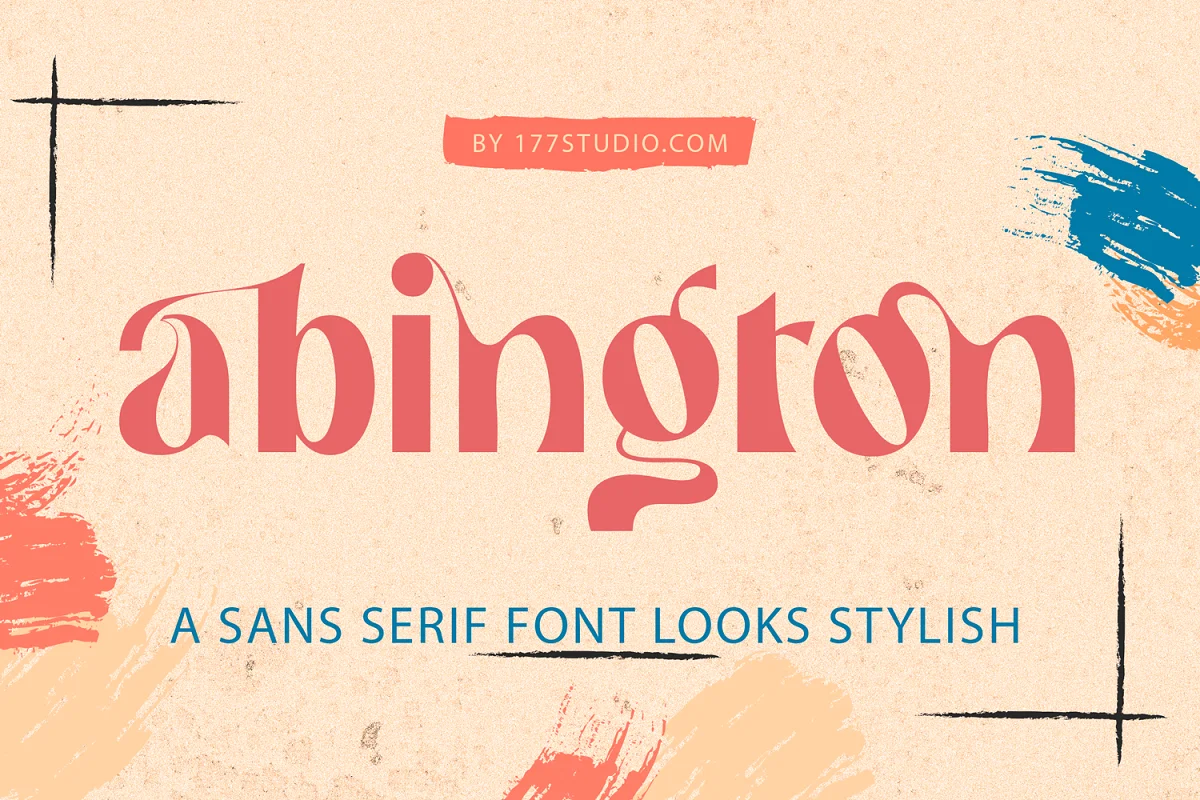
애빙턴은 우아하면서도 모던함과 고풍스러움을 동시에 느낄 수 있는 매력적이고 스타일리시한 모던 서체입니다.
이 산세리프 글꼴은 세련미를 발산하여 브랜딩 프로젝트, 로고, 소셜 미디어 게시물, 광고, 제품 포장, 사진, 초대장, 편지지 및 손글씨 터치가 필요한 모든 프로젝트에 적합합니다.
Abington의 견고한 디자인은 시선을 사로잡으며 읽기 쉽습니다. 그 매력적이고 고풍스러운 스타일은 모든 프로젝트에 개성을 더하는 동시에 우아함의 요소를 유지합니다. 이 글꼴은 전문성을 희생하지 않고 디자인에 개성을 더하고 싶은 사람들에게 적합합니다.
주축대
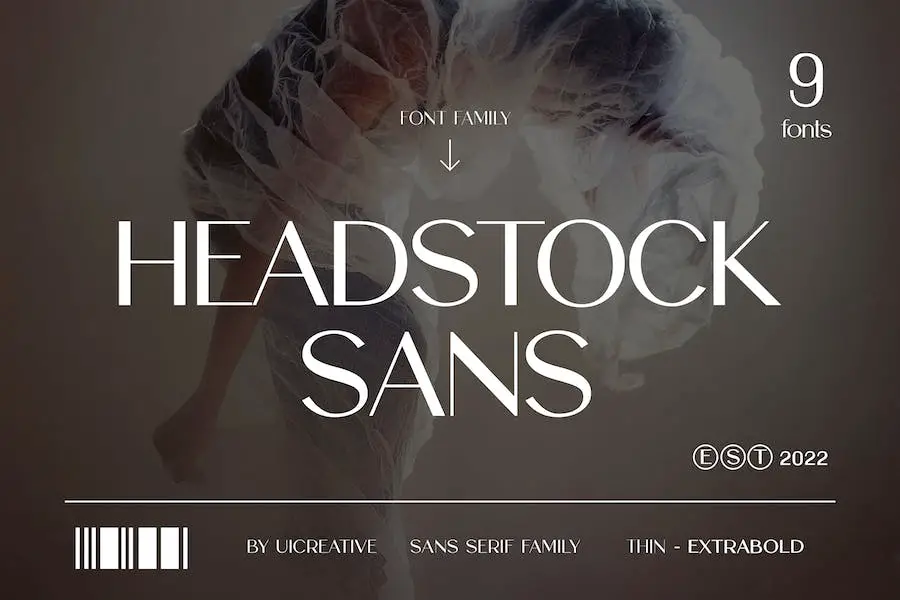
Headstock은 9가지 두께로 제공되는 새로운 Sans Serif 패밀리 글꼴입니다. 현대적이고 우아한 스타일로 문구, 타이포그래피 인용구, 잡지 또는 책 표지, 웹사이트 헤더, 의류, 브랜딩, 포장 디자인 등 다양한 프로젝트에 적합합니다.
남성성과 여성성을 모두 보여주어 패션 관련 브랜딩이나 편집 디자인에 적합합니다.
Google Sans Serif 글꼴에 최적화된 Headstock은 깨끗하고 현대적인 디자인의 현재 트렌드에 완벽하게 맞습니다. 다재다능함과 우아함을 갖춘 이 글꼴은 프로젝트를 향상시키려는 많은 디자이너에게 확실한 글꼴입니다.
에스포르티카
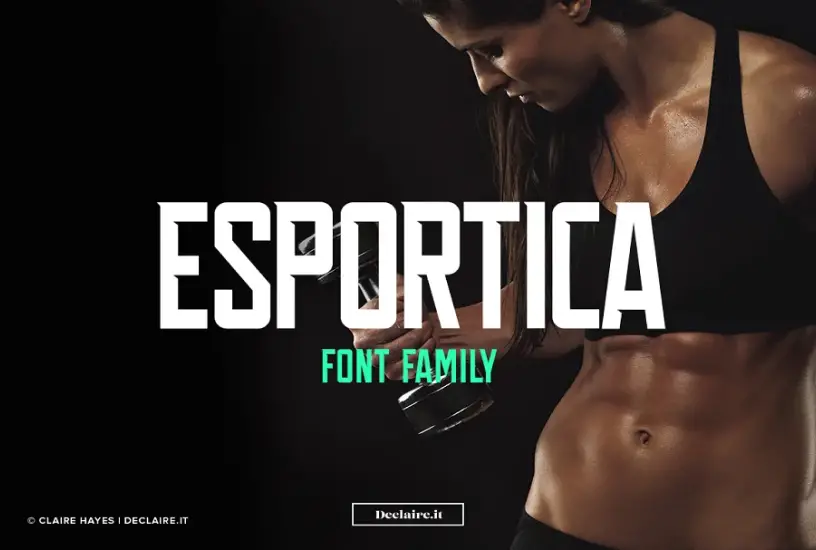
Esportica는 헤드라인에 현대적인 감각을 더할 수 있는 환상적인 디스플레이 서체입니다. 이 서체에는 대문자와 소문자, 구두점, 숫자 등 230개의 글리프가 포함되어 있습니다.
또한 Esportica는 다양한 국제 언어를 지원하므로 디자이너를 위한 다재다능한 글꼴입니다.
Adobe Sans Serif 글꼴과 관련하여 Esportica는 깔끔한 선과 매끄러운 모양으로 인해 탁월한 선택입니다. 날카로운 모서리와 대담한 글자가 있는 이 서체는 모든 디자인 프로젝트에 새로운 수준의 전문성을 제공할 수 있습니다.
풍카시
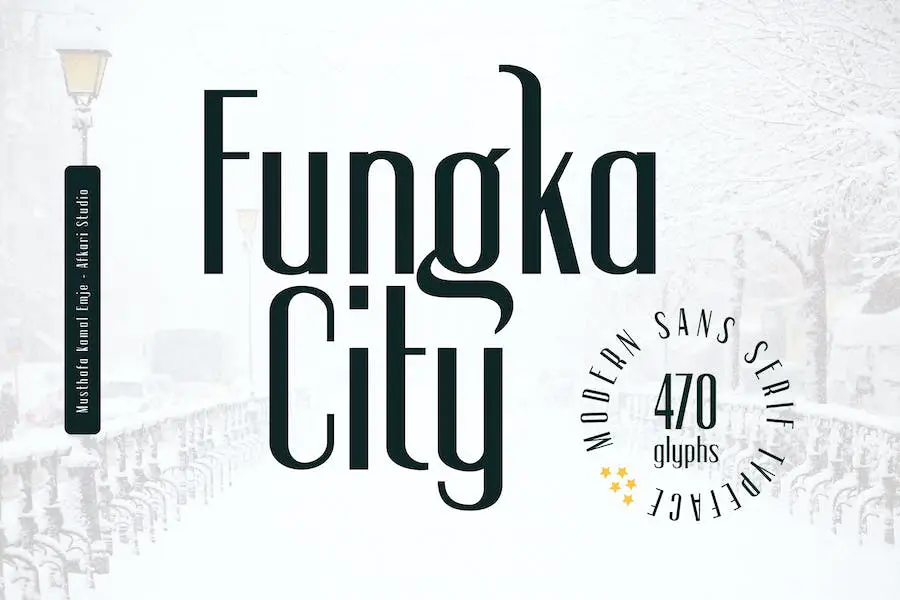
Fungka City는 디자인에 개념적 우위를 부여하는 현대적이고 세련된 산세리프 글꼴입니다. 다른 현대 산세리프체와 잘 어울리지만 독특한 교대 문자와 세련된 악센트로 인해 그 자체로도 두드러집니다.
Word 문서에 사용할 다재다능하고 세련된 산세리프 글꼴을 찾고 있다면 Fungka City를 확실히 고려해 볼 가치가 있습니다. 독특한 디자인과 광범위한 기능으로 인해 모든 디자이너의 툴킷에 추가할 수 있습니다.
메티큘라
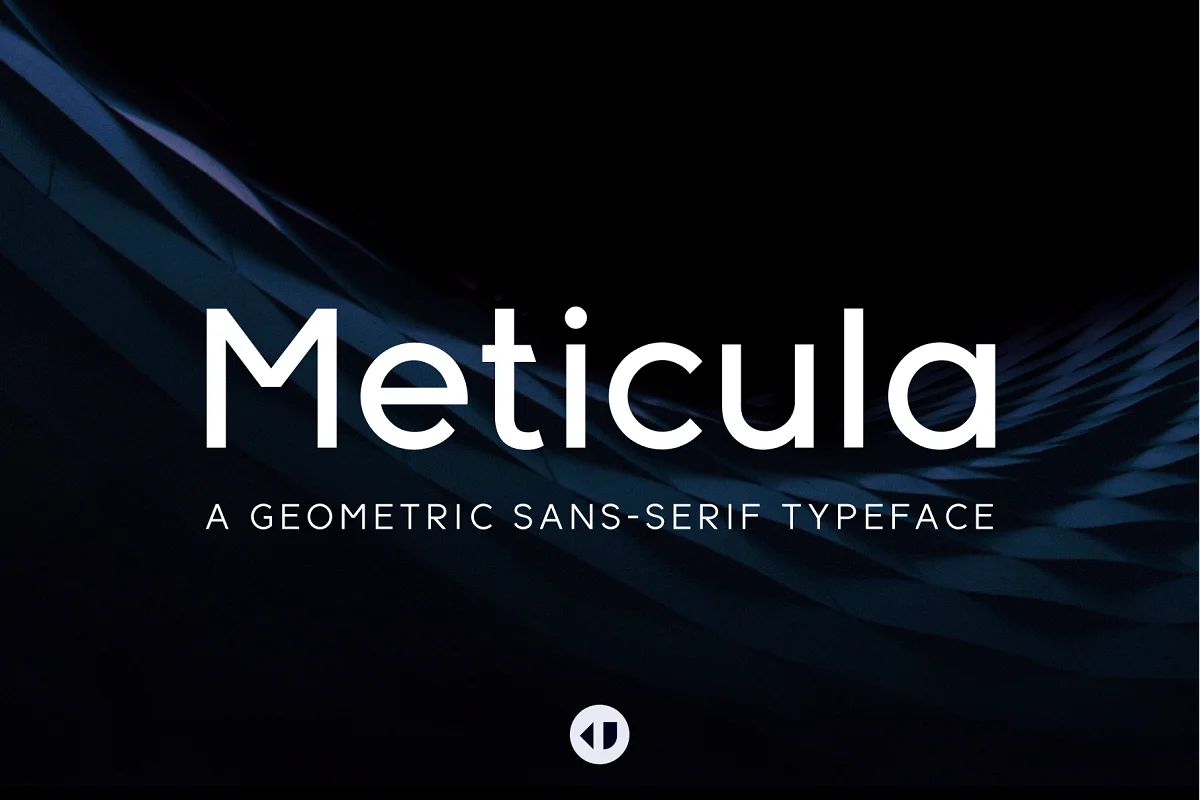
Meticula는 기하학적 모양과 현대적인 타이포그래피를 결합한 다목적 산세리프 글꼴 모음입니다. 18개의 글꼴로 구성되어 있으며 각 글꼴은 모든 유형의 그래픽 디자인 및 타이포그래피 작업에 적합하도록 세심하게 제작되었습니다.
미니멀한 디자인과 다양한 글꼴 스타일을 갖춘 Meticula는 Canva 프로젝트에 사용할 완벽한 산세리프 글꼴을 찾는 그래픽 디자이너에게 탁월한 선택입니다. 글꼴 패밀리의 깔끔한 선과 균형 잡힌 비율은 눈에 띄는 전문적인 디자인을 만드는 데 이상적입니다.
높은
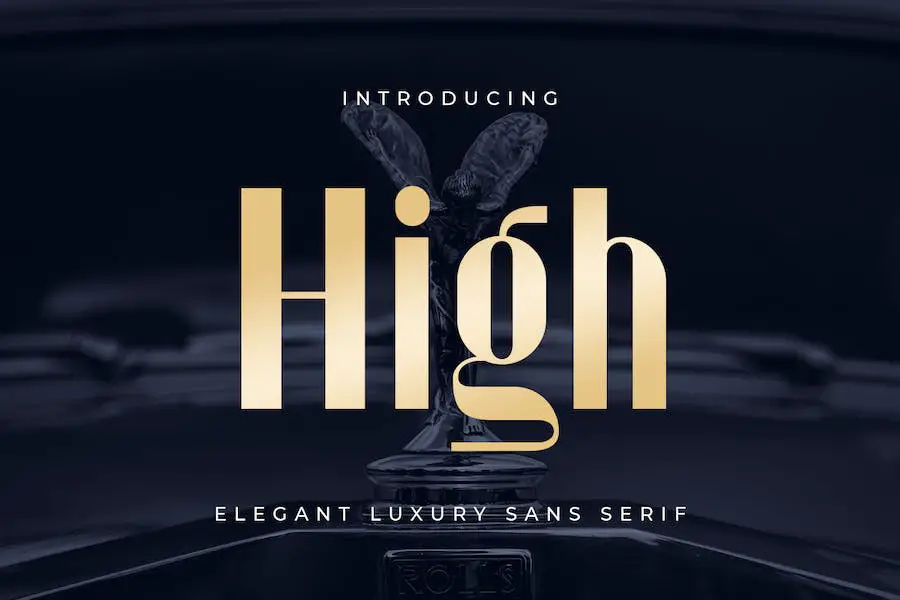
High는 우아한 프로젝트를 진행하는 사람들을 위해 특별히 제작된 새롭고 우아한 고급 산세리프 글꼴입니다.
고유한 모양의 추가 합자와 대체 글꼴이 있는 이 글꼴은 모든 브랜드에 가치를 더할 것입니다. High는 자신의 디자인을 더욱 우아하고 고급스럽게 보이게 하는 솔루션을 찾는 디자이너 또는 제품 소유자를 활용하는 데 도움이 될 수 있습니다.
결론적으로 High는 우아하고 고급스러운 산세리프 글꼴을 찾는 사람에게 환상적인 선택입니다.
고유한 기능으로 인해 약간의 정교함이 필요한 고급 프로젝트 작업에 적합합니다. 브랜드나 프로젝트를 향상시킬 방법을 찾고 있다면 높음 사용을 고려하십시오.
클리오
클리오는 심플하고 깔끔한 선과 시각적인 우아함이 특징인 디스플레이용 산세리프체입니다. 로고, 제목, 잡지와 같은 우아한 테마의 디자인 프로젝트에 적합합니다. 표준 합자를 사용하여 사용자 지정 연결된 문자를 쉽게 만들 수 있습니다.
지노라
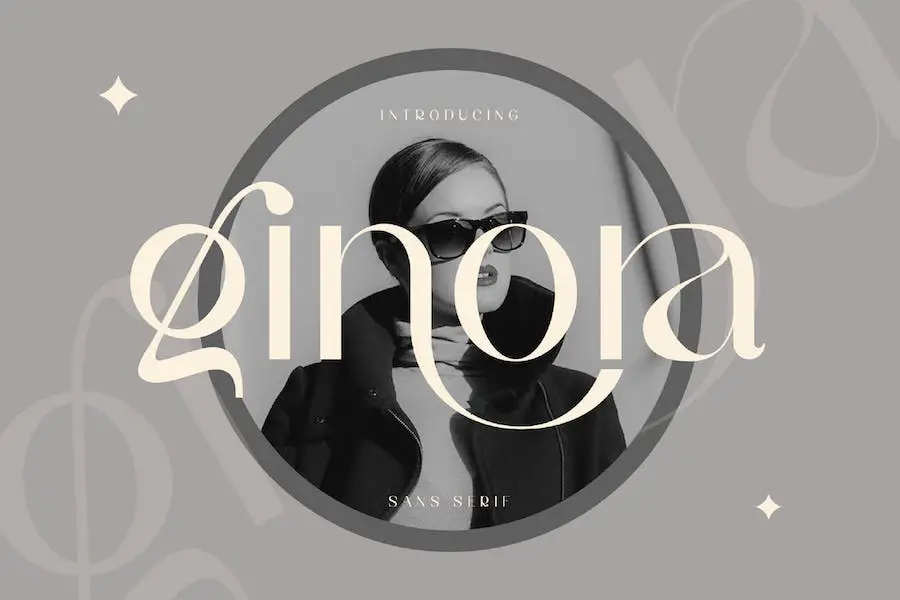
Ginora는 우아함과 품격을 풍기는 세련된 산세리프체입니다. 디자인에 모던함과 향수를 더하고 싶은 분들에게 적합합니다. 이 글꼴은 다목적일 뿐만 아니라 기능적이어서 잡지, 로고, 소셜 미디어 등에 사용하기에 이상적입니다.
결론적으로 Ginora는 프로젝트를 향상시키기 위해 새로운 산세리프 스타일을 찾는 디자이너에게 꼭 필요한 글꼴입니다. 우아하고 유행을 타지 않는 디자인으로 이 글꼴이 창작자들 사이에서 가장 인기 있는 글꼴이 된 것은 놀라운 일이 아닙니다.
숫자, 합자, 구두점 및 언어 지원을 포함한 개방형 기능을 통해 Ginora는 단순한 얼굴 그 이상을 제공합니다. 그리고 그것을 문신 디자인에 통합하려는 사람들을 위해 산세리프 디자인은 텍스트 기반 디자인을 위한 훌륭한 선택입니다.
오스먼드
Osmund는 헤드라인용으로 특별히 제작된 대담한 산세리프 글꼴입니다. 대문자와 소문자를 모두 포함하는 일반 및 원형의 두 가지 뚜렷한 스타일로 제공됩니다.
새싹
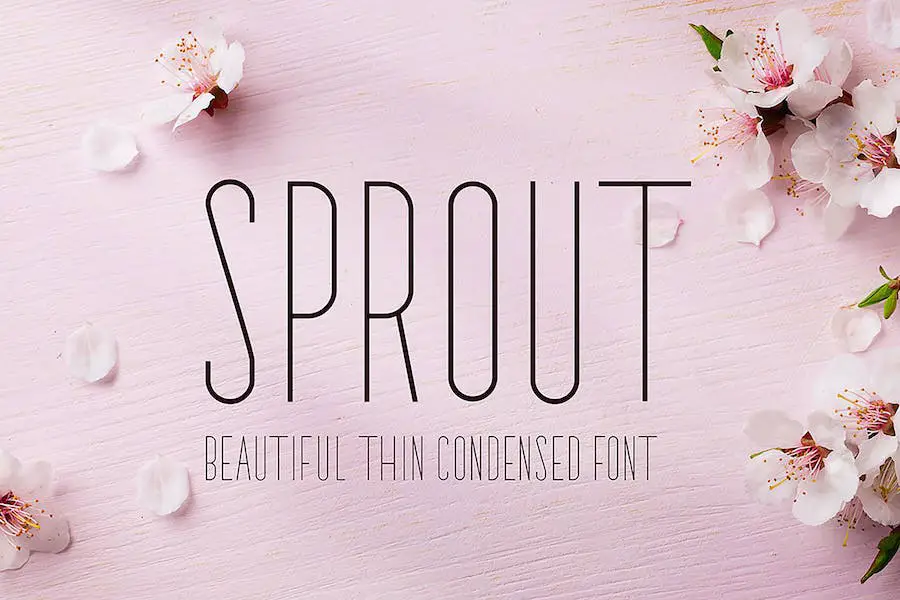
Sprout는 우아한 Thin Condensed Sans Serif 글꼴로 결혼식 디자인, 초대장, 웹사이트 등에 적합합니다. 이 아름다운 글꼴은 대문자와 소문자를 특징으로 하며 영어, 포르투갈어, 스페인어 및 프랑스어에 대한 언어 지원을 포함합니다.
전반적으로 다재다능하고 사용하기 쉬운 우아한 산세리프 글꼴을 찾고 있다면 Sprout를 확인해 볼 가치가 있습니다. 아름다운 디자인과 다국어 지원으로 글꼴 라이브러리에 귀중한 추가 기능이 될 것입니다.
문 차일드
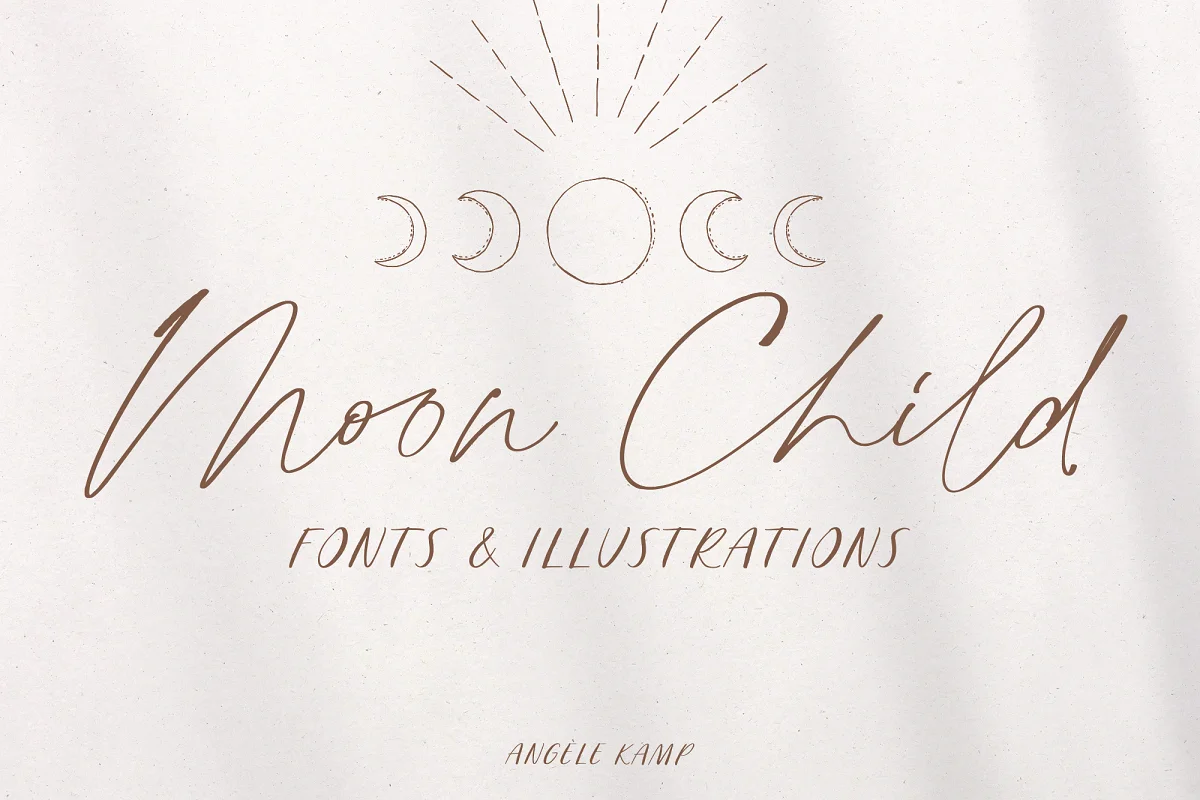
Moon Child는 당신의 디자인을 한 단계 더 끌어올릴 아름다운 글꼴과 일러스트레이션 모음입니다. 두 개의 완벽하게 짝을 이루는 글꼴과 19개의 손으로 그린 삽화가 포함된 이 컬렉션은 Instagram, 인용문, 웹사이트, 초대장 등을 디자인하는 데 적합합니다.
Moon Child를 사용하면 바로 디자인을 시작하고 정말 독특한 것을 재미있게 만들 수 있습니다. 그래픽 디자이너이든 아마추어 예술가이든 이 컬렉션에는 비전을 실현하는 데 필요한 모든 것이 있습니다. Modern Sans Serif 글꼴을 사용하는 것이 그 어느 때보다 쉬워졌습니다!
후드저
Hoodger는 각 문자에 깔끔함을 약속하는 현대적이고 우아한 산세리프 글꼴입니다.
깔끔한 선으로 Hoodger는 포스터, 배너, 로고, 초대장, 잡지 표지, 인용구, 제목, 인쇄물, 소셜 미디어 등 다양한 디자인 프로젝트에 사용할 수 있는 다목적 글꼴로 돋보입니다.
전반적으로 Hoodger는 모든 디자이너의 툴킷에 탁월한 추가 기능을 제공하며 깔끔함과 현대성은 상업용으로 사용하기에 탁월한 옵션입니다.
다재다능하고 사용하기 쉬운 Hoodger는 우아한 터치로 작업을 향상시키려는 디자이너가 찾는 글꼴이 될 것입니다.
착륙
Landing은 대담한 표현을 만드는 독특한 합자 산세리프 글꼴입니다. 높은 콘트라스트와 스타일리시한 디자인으로 브랜딩 및 편집 프로젝트에 다양하게 사용할 수 있습니다. 글꼴의 보기 좋은 모양과 부드러운 느낌은 어떤 계획에도 세련미를 더해줍니다.
Landing의 뛰어난 기능 중 하나는 글자 사이의 원활한 흐름을 만드는 합자입니다. 세부 사항에 대한 이러한 관심은 다른 산세리프체와 차별화되어 헤드라인 및 로고 디자인에 적합합니다. 또한 높은 콘트라스트 덕분에 어두운 배경과 밝은 배경 모두에서 쉽게 읽을 수 있습니다.
후퇴
Throwback은 다양한 디자인 프로젝트에 개성과 독창성을 더할 수 있는 다재다능하고 현대적인 Sans Serif 글꼴입니다.
Throwback의 가장 눈에 띄는 기능 중 하나는 깨끗하고 미니멀한 디자인으로 현대 프로젝트에 탁월한 선택입니다.
명확하고 읽기 쉬운 글자로 된 이 글꼴은 명확하고 정교하게 메시지를 전달하는 데 적합합니다. 또한 Throwback은 여러 가지 무게와 스타일로 제공되므로 특정 요구 사항에 따라 쉽게 조정하고 사용자 정의할 수 있습니다.